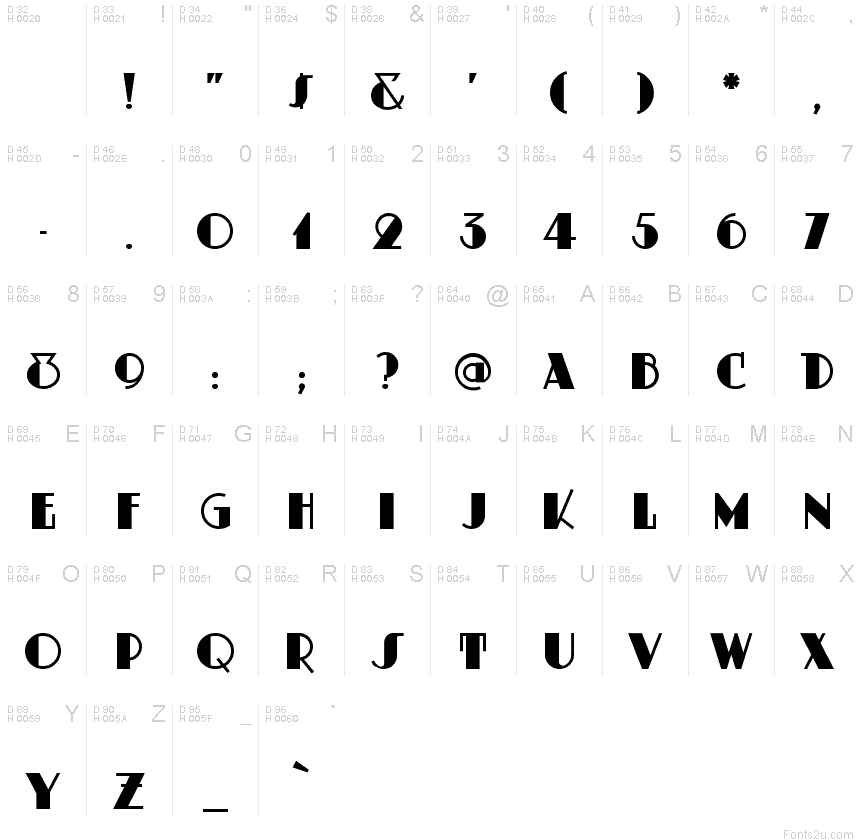
Dusty Rose od Nicka Curtisa to darmowy, retro krój wyświetlaniowy o bujnym, efektownym rytmie, przywodzącym na myśl szyldy kin z połowy XX wieku. Wysokie, blokowe trzonki przecinają miękkie, nasycone krzywizny, a przycięte łuki i ciasne odstępy nadają każdemu słowu elegancką, plakatową sylwetkę. Subtelny sznyt Art Deco sprawia, że litery idealnie do siebie pasują, tworząc wyraziste, ciągłe kształty słów, które pozostają czytelne nawet z dużej odległości.
Dzięki Dusty Rose nadasz plakatom, okładkom książek, grafikom płyt jazzowych lub lounge, brandingowi butików, opakowaniom i grafikom w mediach społecznościowych w stylu vintage natychmiastowy, filmowy charakter. Ten darmowy font błyszczy w dużym rozmiarze, pozwalając wybrzmieć swoim rzeźbiarskim krzywiznom; w tekście głównym zestaw go z prostym krojem bezszeryfowym, aby retro dramaturgia pozostała tam, gdzie jej miejsce – w nagłówkach.